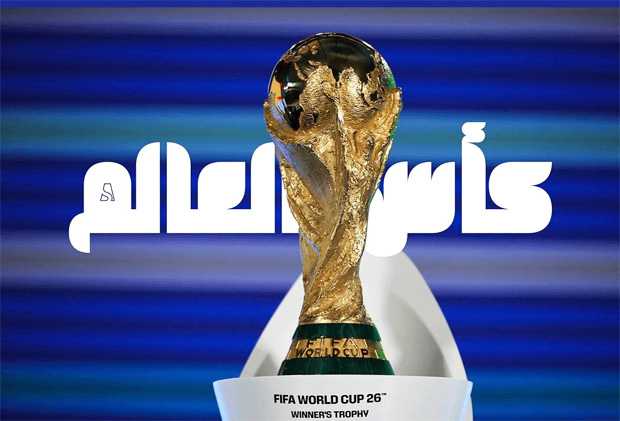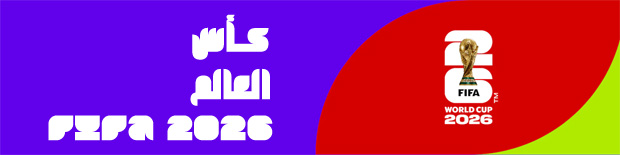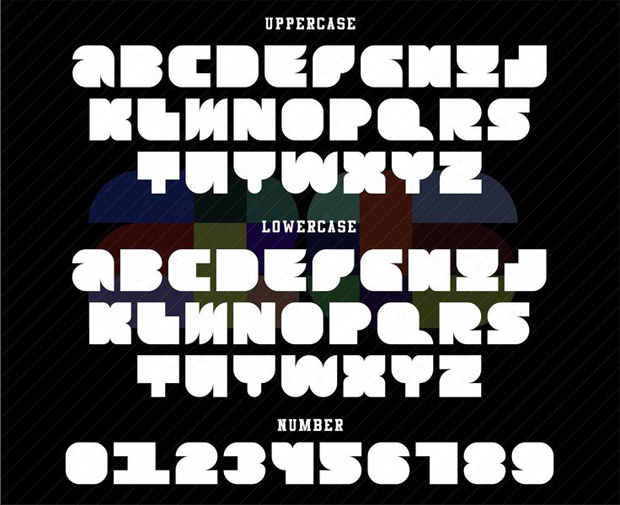
خط فيفا كأس العالم 2026 العربي والإنجليزي .. الخط الشهير لكأس العالم 2026 باللغة الإنجليزية وباللغة العربية، يمكن استخدامه في التصميم والبنرات والتيشرتات وكافة الملحقات الخاصة بكرة القدم العالمية، وهو متاح للتحميل المجاني الان.